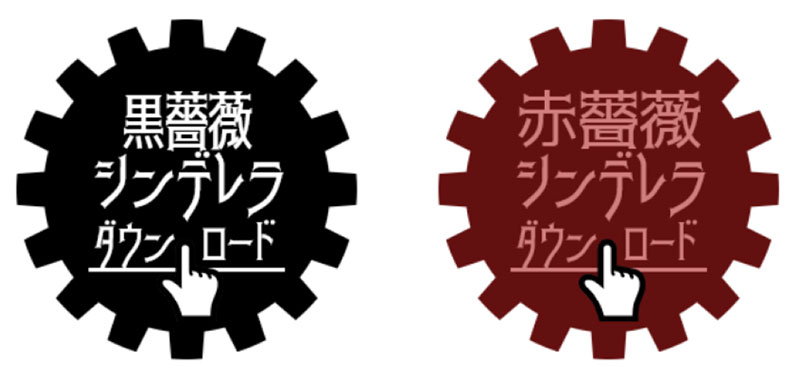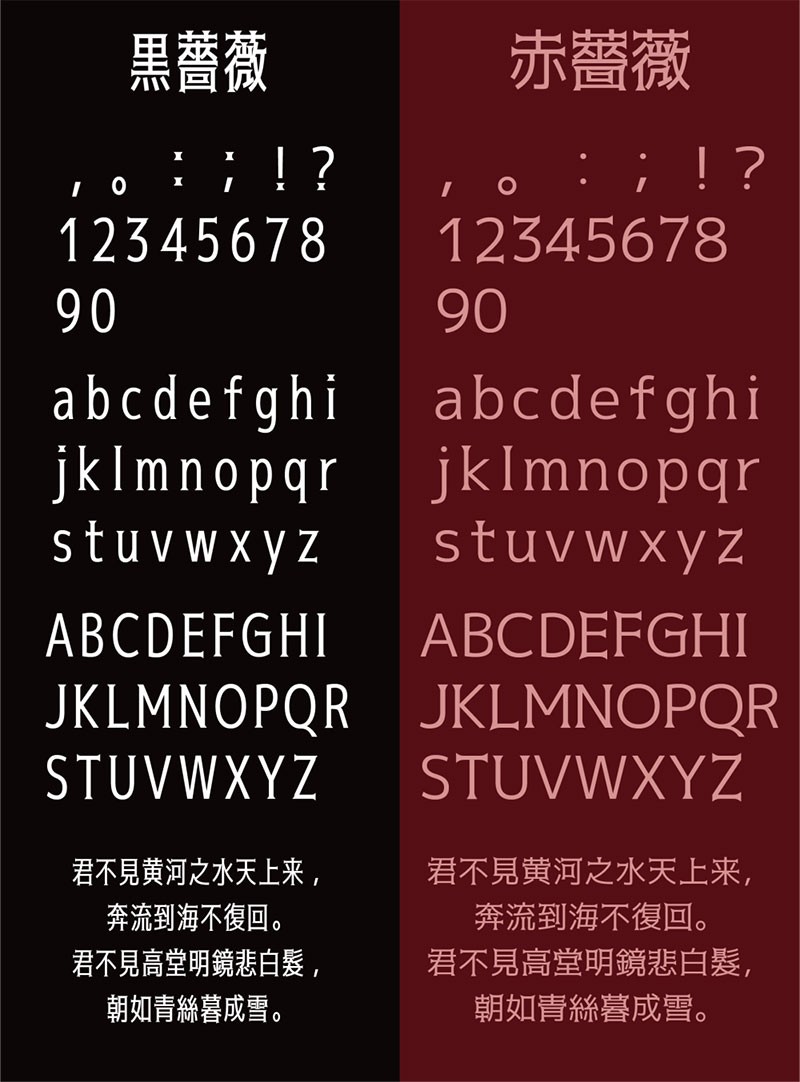
黒薔薇和赤薔薇日文字体,免费可商用
一款充满魔幻神秘色彩的日文字体,具有强烈的视觉冲击力,每个字形都有小尖角形状的设计,比较适合有个性的氛围,也适应于杂志、书籍常用字体, 海报、个性品牌标志设计、字体设计等环境使用。部分中文简体字无法显示,切换到繁体输入即可。
这款字体分为两个版本。分别是 黒薔薇(日文名: 黒薔薇シンデレラ )和赤蔷薇(日文名: 赤薔薇シンデレラ )两款。这两款的区别是, 黒薔薇的字体比较纤细,而赤薔薇的字体比较宽。